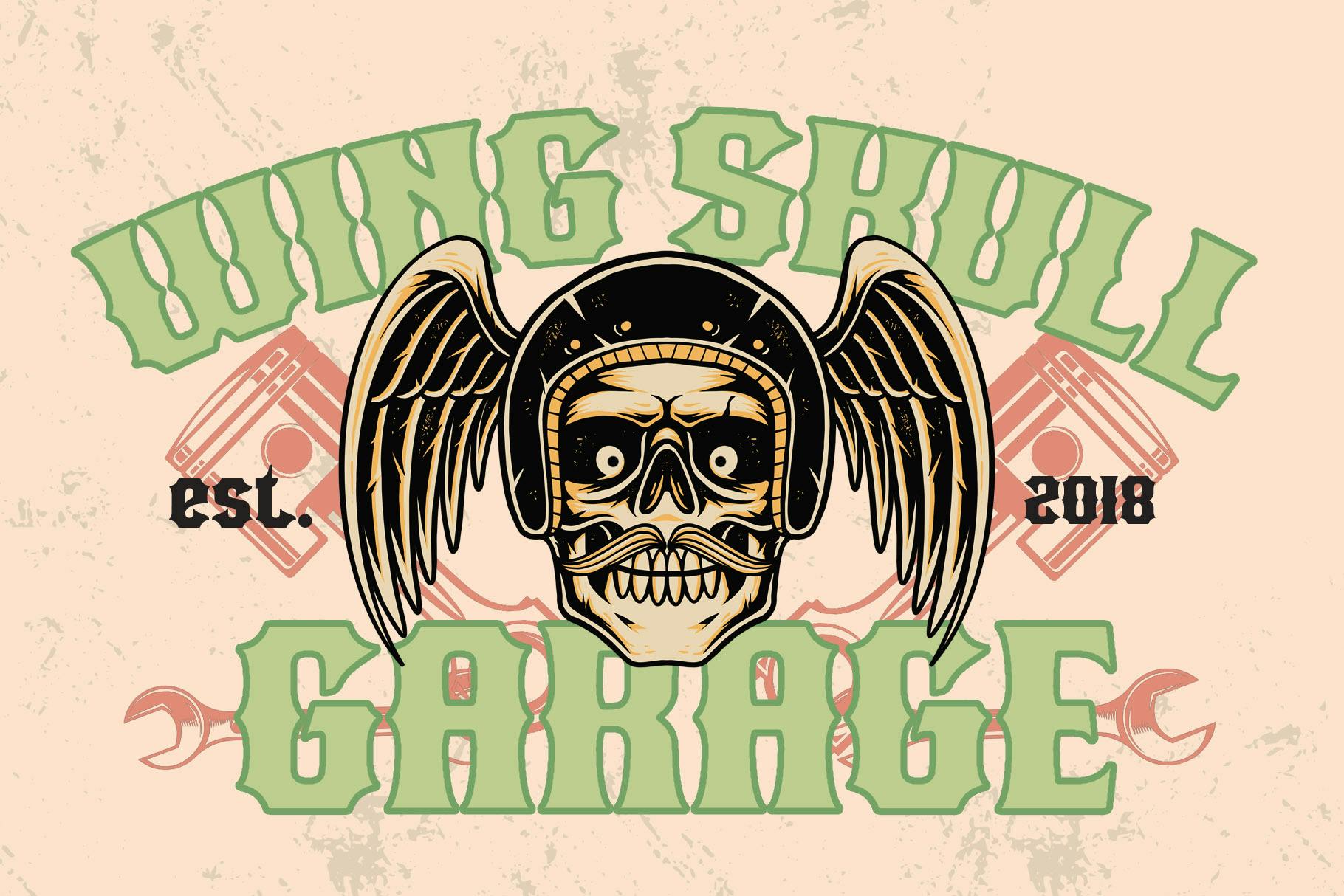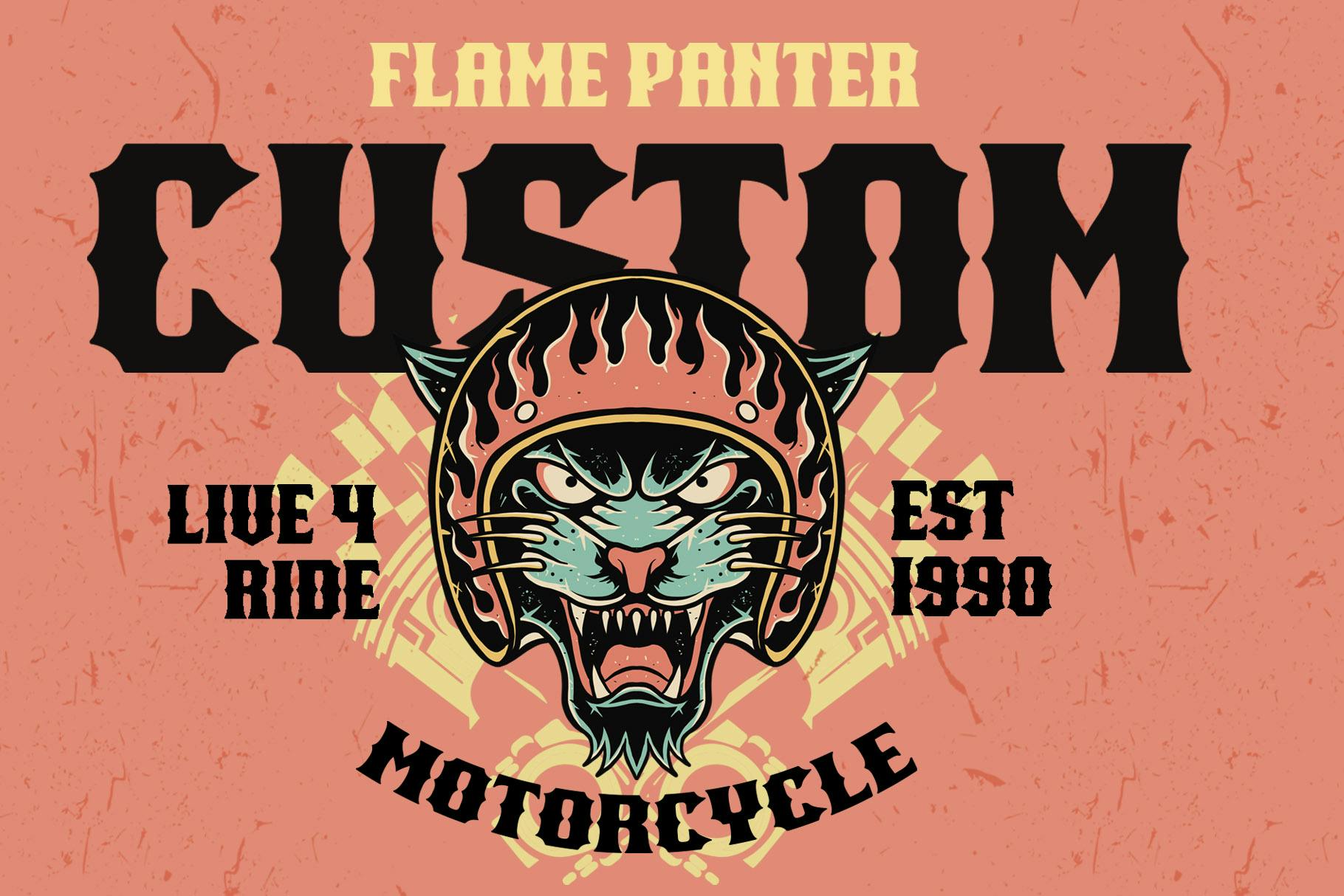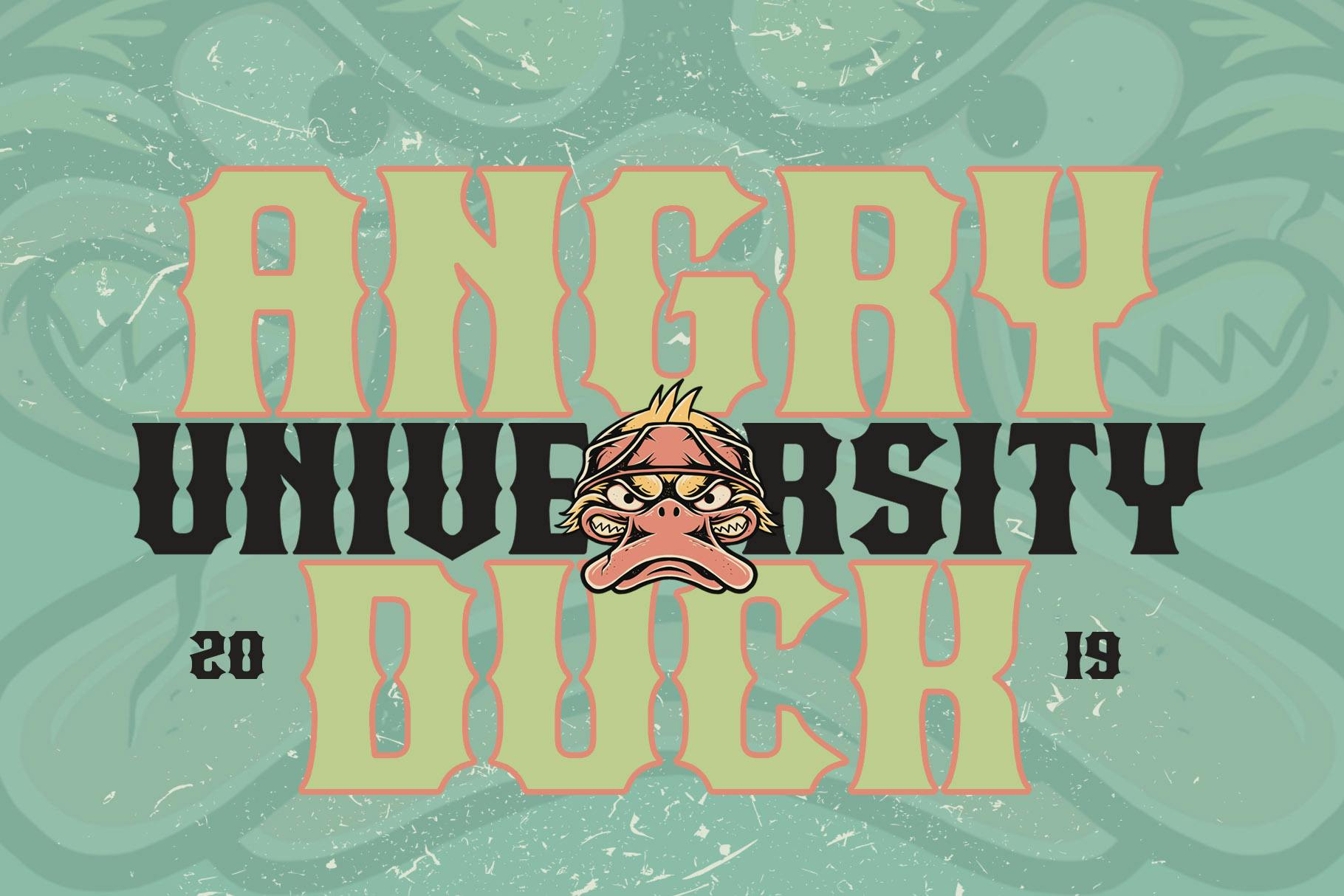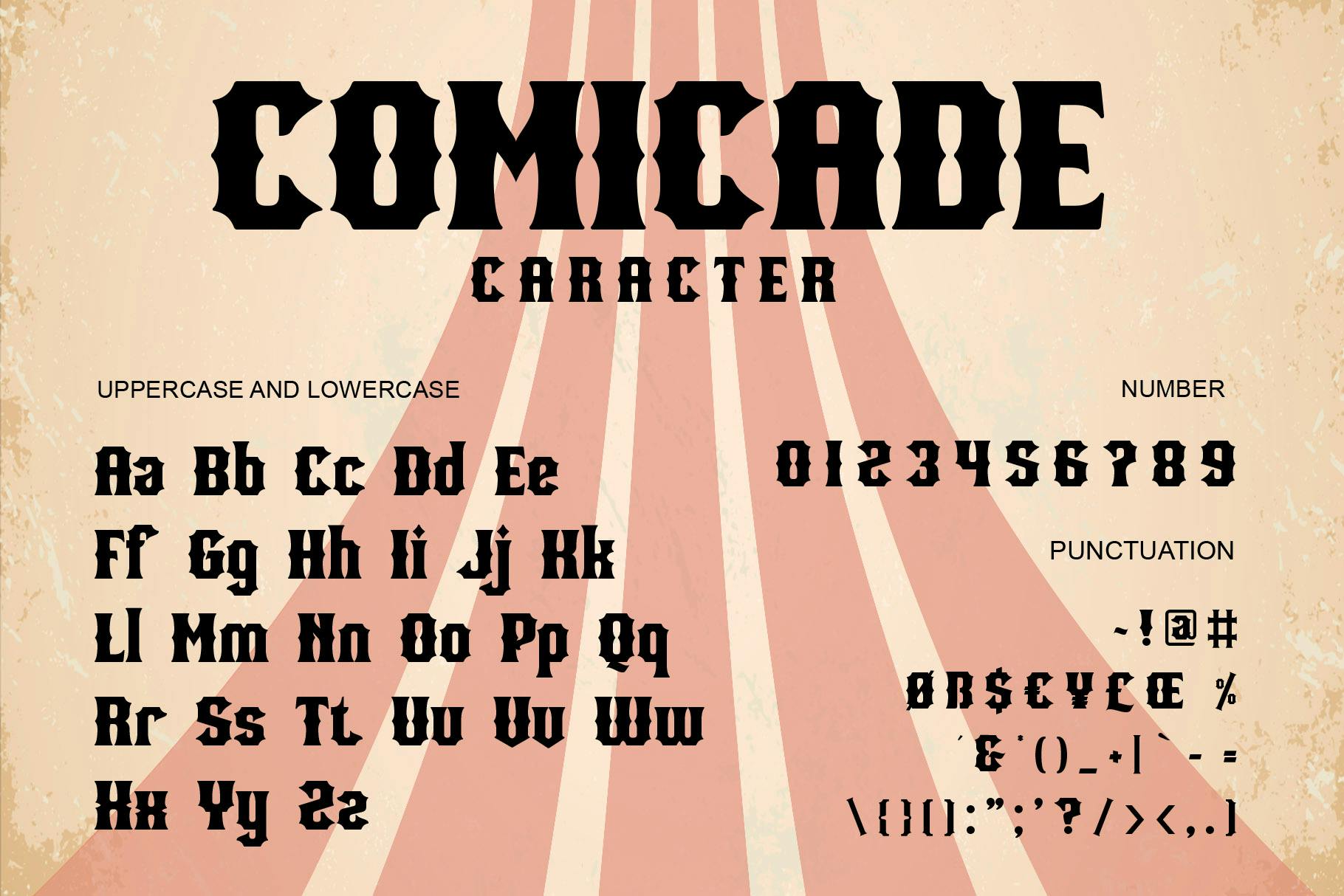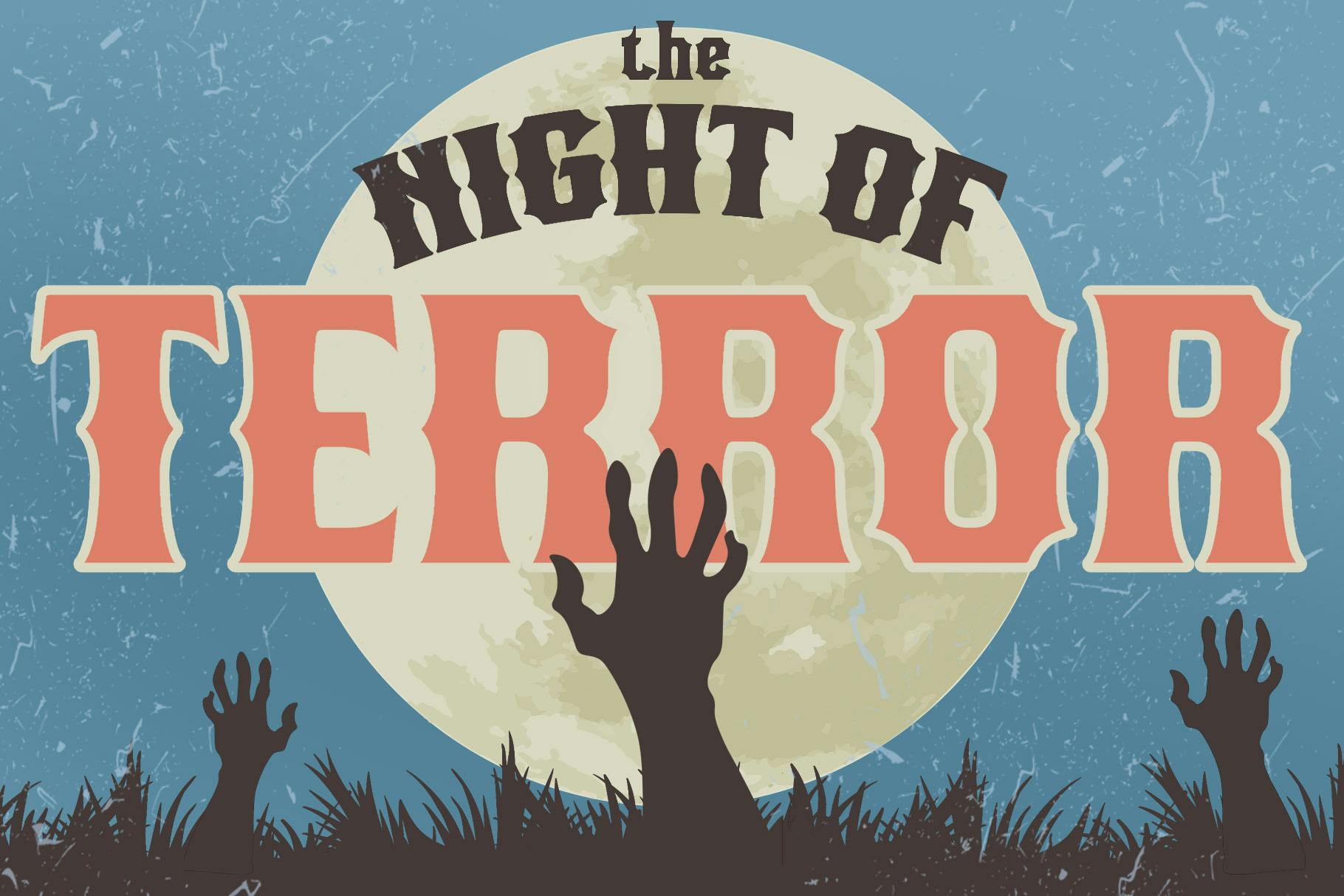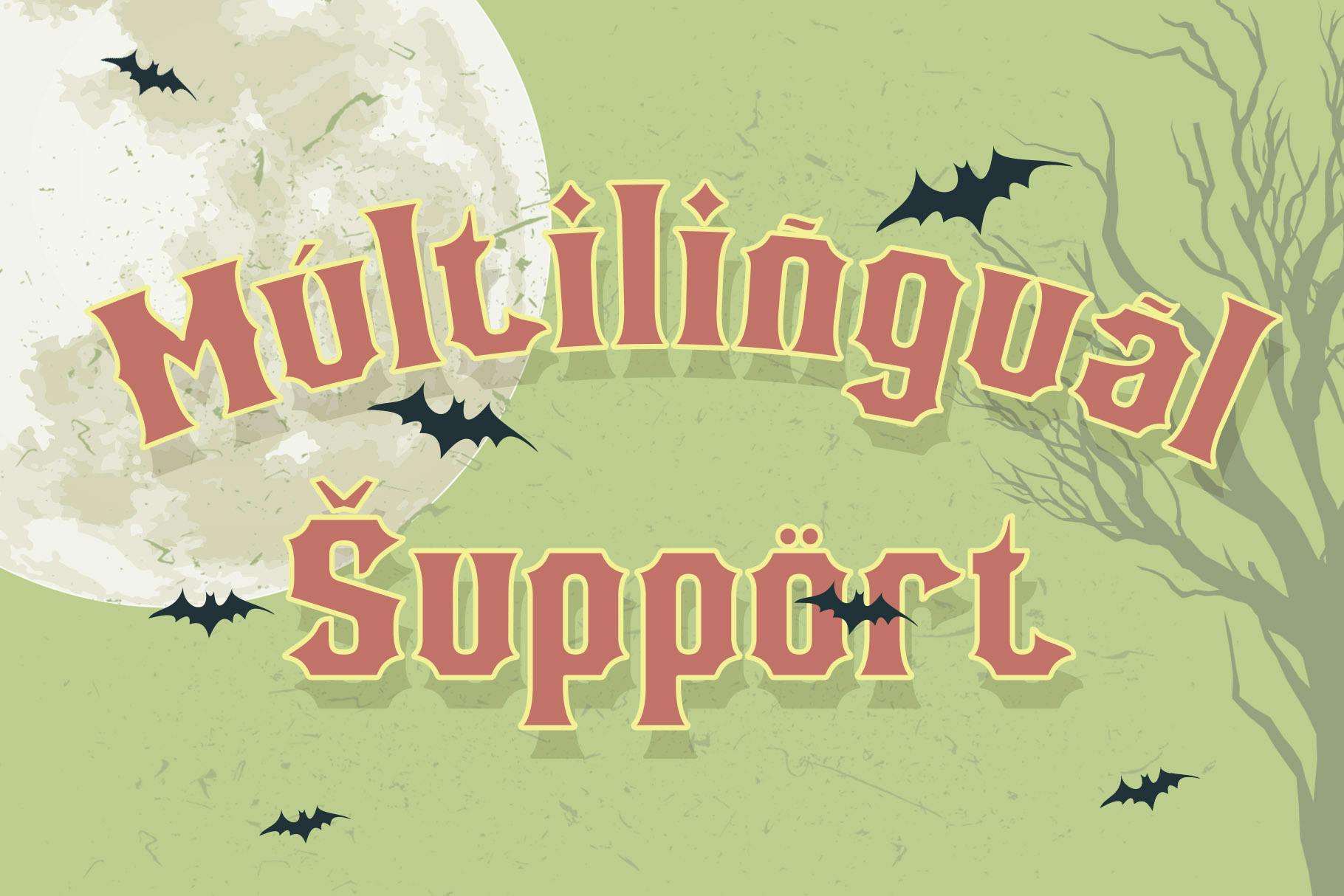
فونت کامیکید (Comicade Font)
این فونت الهام گرفته از طراحی پوسترهای کارتونی قدیمی است که در برخی کافهها مشاهده کردم. این فونت بهصورت دستی طراحی شده تا احساس طبیعی و دستساز را در هویت برند ایجاد کند و سپس با استفاده از ابزار پنتول بهصورت تمیز و دقیق ساخته شده است.
ویژگیهای اوپنتایپ
فونت کامیکید دارای مجموعه کاراکتر ۲۰۵ تایی است. این فونت در طراحی لوگو، برچسبها، بستهبندی محصولات، دعوتنامهها، تبلیغات و دیگر پروژهها بسیار زیبا به نظر میرسد.